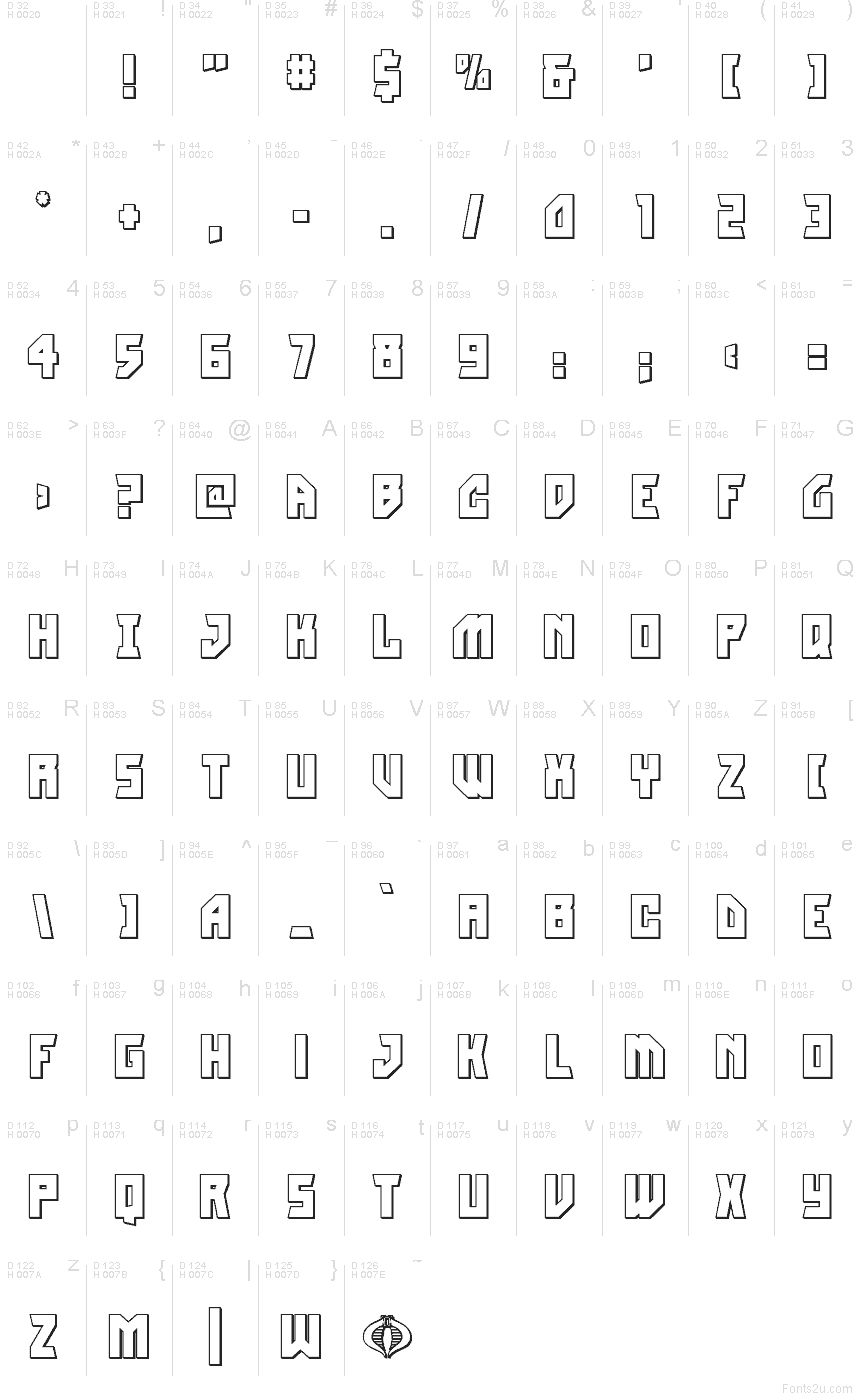
Omni-cobra Straight 3D
Omni-Cobra Straight 3D de Iconian Fonts es una tipografía techno display gratuita, con una estructura cuadrada estilo arcade y un tratamiento 3D integrado en sus bordes. Sus formas presentan lados rectos, esquinas afiladas y una línea central hueca que otorga a todo el conjunto un aspecto mecánico de corte industrial.
Omni-Cobra Straight 3D funciona muy bien en títulos de videojuegos, pósteres de ciencia ficción, logotipos, arte de álbumes y titulares donde se busque una forma rígida y bien diseñada. Su construcción angular también la hace ideal para elementos de marca, gráficos de eventos y textos breves que requieran un estilo futurista de líneas definidas.